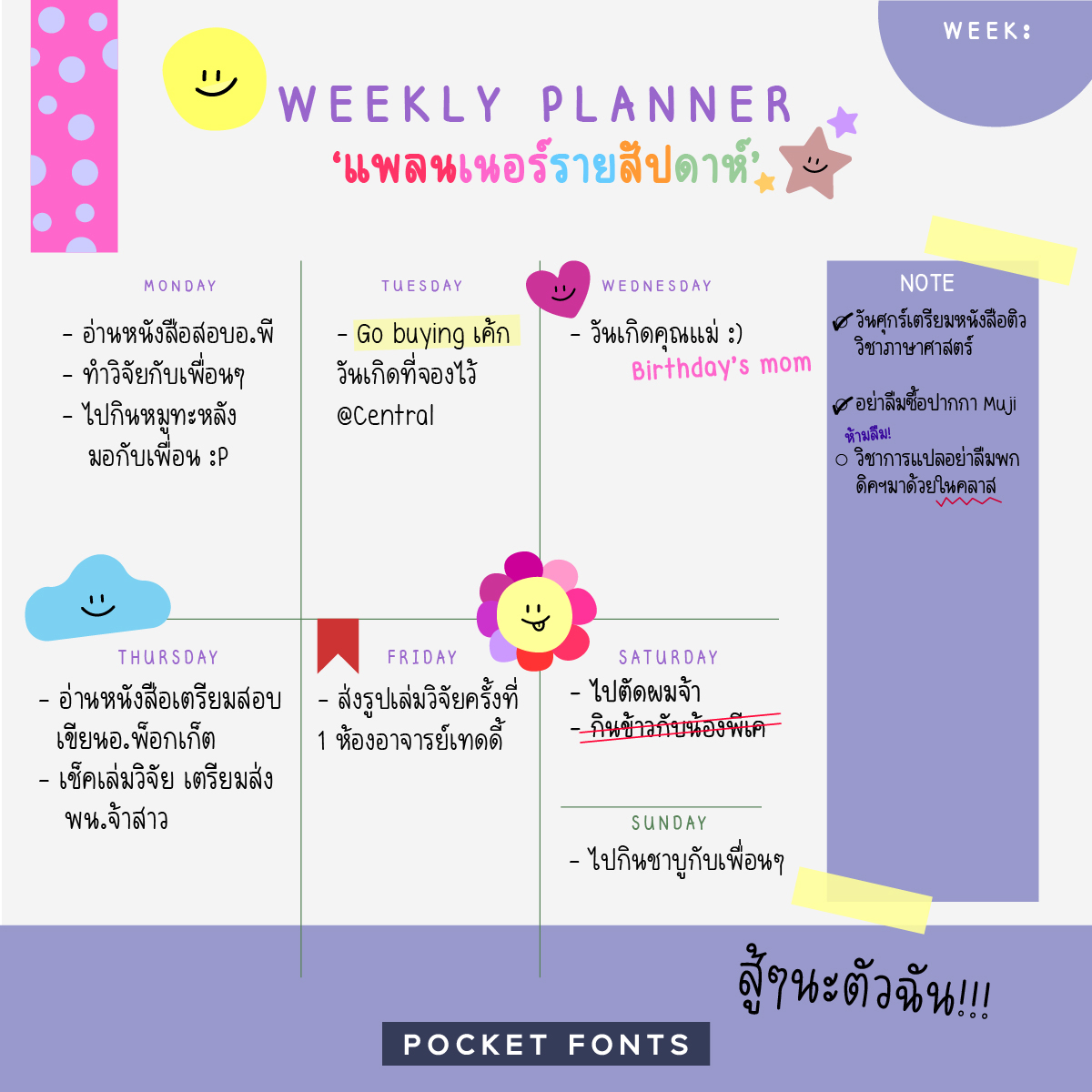
PK Samut Songkhram
ชื่อฟอนต์: พีเค สมุทรสงคราม | PK Samut Songkhram
ฟอนต์ พีเค สมุทรสงคราม เริ่มจากการที่เป็นคนชอบจดและเขียนหนังสือมากๆคนนึง ชอบจดเลคเช่อร์ตอนเรียนรวมถึงจดโน็ตต่างๆในชีวิตประจำวัน มักใช้การเขียนมากกว่าการพิมพ์ พอถึงช่วงที่ยุคสมัยเปลี่ยนไป เรียนจบแล้วก็ไม่ค่อยได้ใช้ปากกาจดเท่าไหร่ จะกลายเป็นใช้การพิมพ์ทุกอย่างลงโน็ตและแพลนเนอร์ออนไลน์แทนเลยเริ่มอยากจะมีฟ้อนต์ที่มีลายมือของตัวเอง จึงเกิดฟอนต์นี้ขึ้นมา